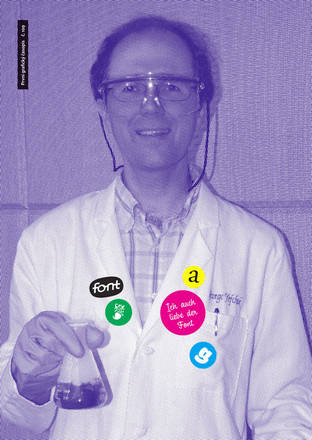
Font 109 :: 1/2010 :: téma: Výzkumné ústavy
Adéla Svobodová |
rozhovor s absolventkou pražské AVU, mj. autorkou grafického stylu Fresh Film Festu |
Global Crisis |
3. virtuální bienále grafického designu a výtvarného umění v pražské galerii Altán Klamovka |
Neue Frutiger |
Akira Kobayashi ve spolupráci s Adrianem Frutigerem přepracovali Frutiger z roku 1977 |
Pavel Ctibor: korálky atomů TiO2 |
vědecký pracovník vystavuje pevné látky extrémním tepelným účinkům, pak je pozoruje a fotografuje |
Kakao Black / Cursive / Script |
pokračování série prezentací nových českých písem |
AČRA, pecky a krize… |
rozhovor s prezidentem Asociace reklamních agentur Mgr. Pavlem Brabcem |
METRo Zlatá pecka 2009 |
vyhlášení výsledků 15, ročníku soutěže kreativní reklamní tvorby |
Resonance |
2. místo v kategorii Knihy o výtvarném umění, obrazové a fotografické publikace v soutěži NČKR 2008 |
L’Atlas – městský výhybkář |
rozhovor se špičkovým francouzským street artovým umělcem |
Dresing.org |
rozhovor s přispěvatelem do Fontu Petrem Mazochem |
CI výzkumných ústavů |
vizuální styl světových i českých výzkumných ústavů |
Vlnovka pro fotoniku |
vizuální styl Ústavu fotoniky a elektroniky Akademie věd z roku 2007 |
Vizuální styl VÚTS |
Computer design studio provedlo redesign loga a vytvořilo novou CI v roce 2007 |
TC má nový grafický styl |
Technologické centrum a jeho nová identita od Martina Procházky ze studia Creature |
Loga výzkumných ústavů |
tradiční rubrika s hodnocením značek |
City Pro |
pravidelné ukázky písem |
Kurz pro fotografy, |
Byznys kurs pro fotografy pořádala isifa Image Service |
Reklama, Polygraf 2010 |
důvody, proč navštívit letošní ročník renomovaného veletrhu |
Monitory, digitální tisk, skenery, |
Anketa výrobců a dodavatelů periferií pro profesionální pracoviště |
Test tiskárny OKI ES9410 |
účelné a rentabilní tiskové řešení pro malonákladový tisk |
Produkční tiskové stroje |